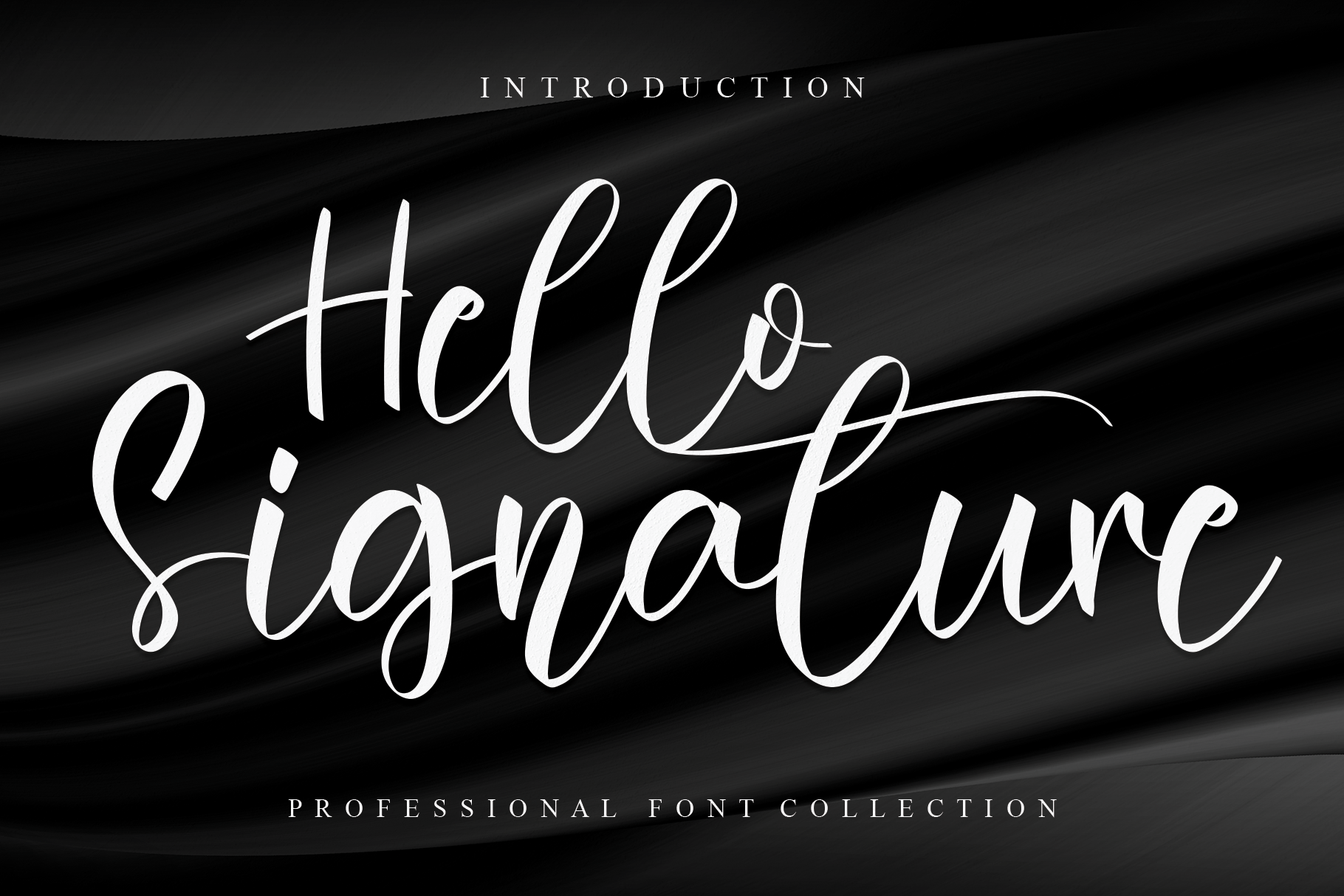
Hello Signature Font – Fonte Grátis
Hello Signature Font
A Hello Signature Font é uma seleção única criada para quem deseja adicionar um toque elegante a suas produções digitais e impressas. Com seus traços naturais e elegantes, esta fonte personalizada oferece uma experiência de escrita autêntica que vai ao encontro dos mais exigentes estilos contemporâneos. Perfeita para criação de embalagens, logotipos para redes sociais ou posts publicitários, este design é versátil o suficiente para se adaptar a múltiplas categorias e formatos. Seja em uma pequena etiqueta, um post impresso ou até mesmo como marcas legais no fundo de imagens, a Hello Signature Font traz seu estilo autêntico e personalizado ao trabalho que você faz. A Hello Signature Font não só oferece um upgrade em termos de design para seus projetos digitais e impressos, mas também permite criar algo realmente único. Seja uma etiqueta de produto elegante ou até mesmo uma assinatura para cartas pessoais, este é o tipo de fonte que transforma qualquer projeto com seu toque único e profissional. Estamos entusiasmados em oferecer a Hello Signature Font como parte da nossa linha de fonts criativas. Cada caracter exibe um toque autêntico e humano, garantindo que sua marca ou produto seja reconhecível e se destaque na multidão.